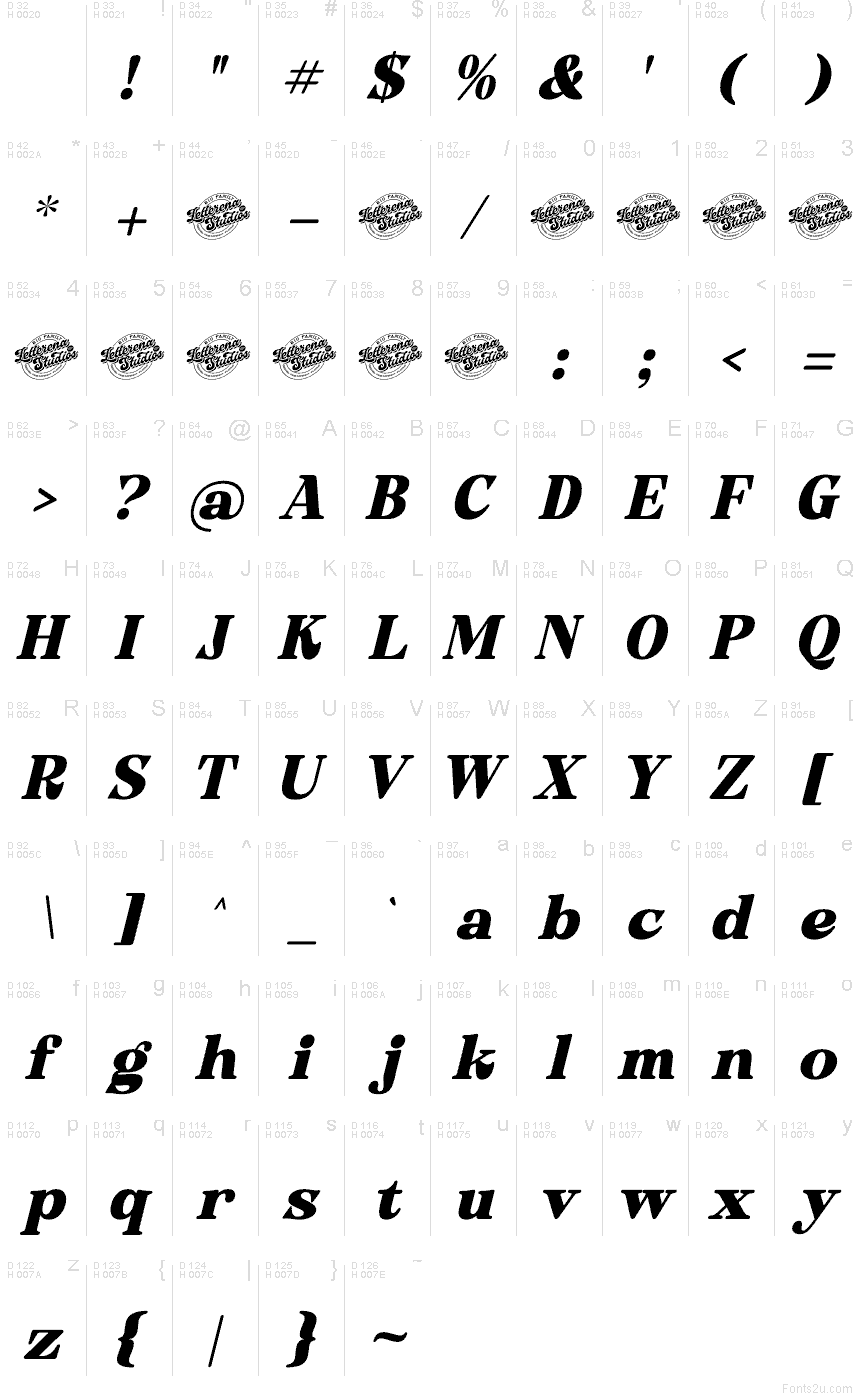
Begsta Pearl DEMO VERSION Italic
Begsta Pearl von Letterena Studios ist eine kostenlose, romantische Serifenschrift im Kursivstil, die mit weit geschwungenen Kurven und einem Hauch von Vintage-Eleganz besticht. Die Buchstaben sind stark geneigt und wirken eher weich und üppig als scharf gezeichnet. Ein Spiel aus kräftigen Kontrasten, abgerundeten tropfenförmigen Details und charakteristischen Schnörkeln verleiht dieser Schrift ihren kunstvollen Rhythmus.
Sie eignet sich hervorragend für Boutique-Branding, Kosmetikverpackungen, Magazin-Cover, Café-Menüs und Hochzeitspapeterie – überall dort, wo die geneigte, modische Silhouette für echte Persönlichkeit sorgt. Da es sich um eine kostenlose Schrift handelt, ist sie zudem ideal für Titelkarten, Social-Media-Grafiken und kurze Zitate, wenn Sie einen eleganten, aber dennoch verspielten Look suchen.